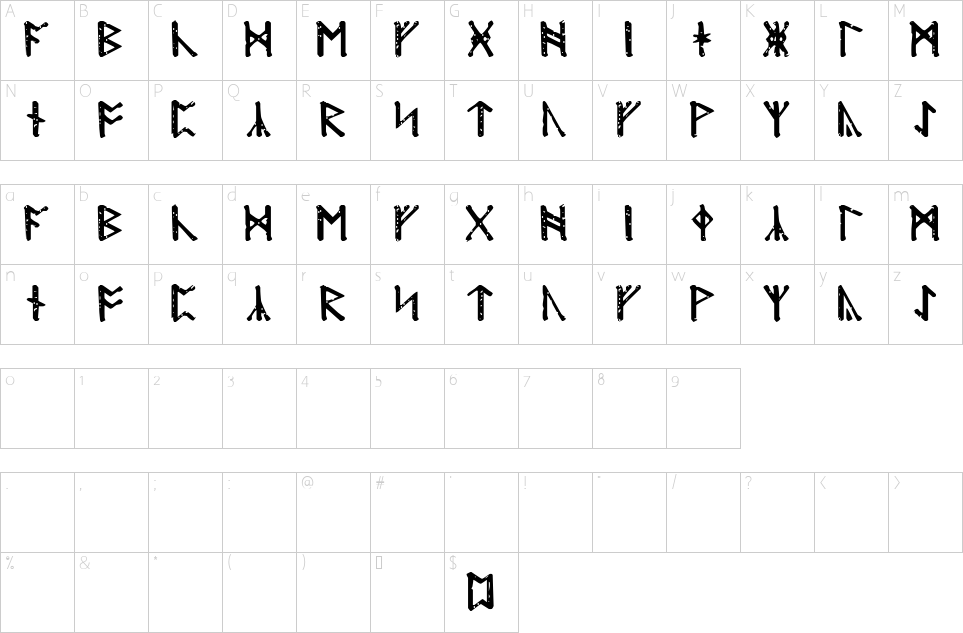
A fonte Modraniht Runic é uma herança do universo antigo, resgatada e adaptada para os tempos atuais. Desenvolvida por Hanoded, essa fonte traz uma atmosfera escura e misteriosa, ideal para aplicar em designs gráficos que buscam uma aparição rústica e elegante. Com seu design cuidadosamente elaborado, Modraniht Runic oferece uma mistura perfeita de elegância e originalidade. Seja para projetos de marca, letras de música ou até mesmo para letras de livros, essa fonte é perfeita para criar um efeito único. Disponível tanto para Windows quanto para Mac, Modraniht Runic font é o recurso gráfico que você precisa para dar um toque inovador em seus projetos. Desenvolvida por Hanoded, essa fonte se destaca entre as muitas opções de fontes gratuitas disponíveis. Ao baixar Modraniht Runic, você não apenas adiciona um novo recurso à sua paleta de fontes, mas também se une a um grupo crescente de criadores que valorizam a criatividade e a inovação no design gráfico.